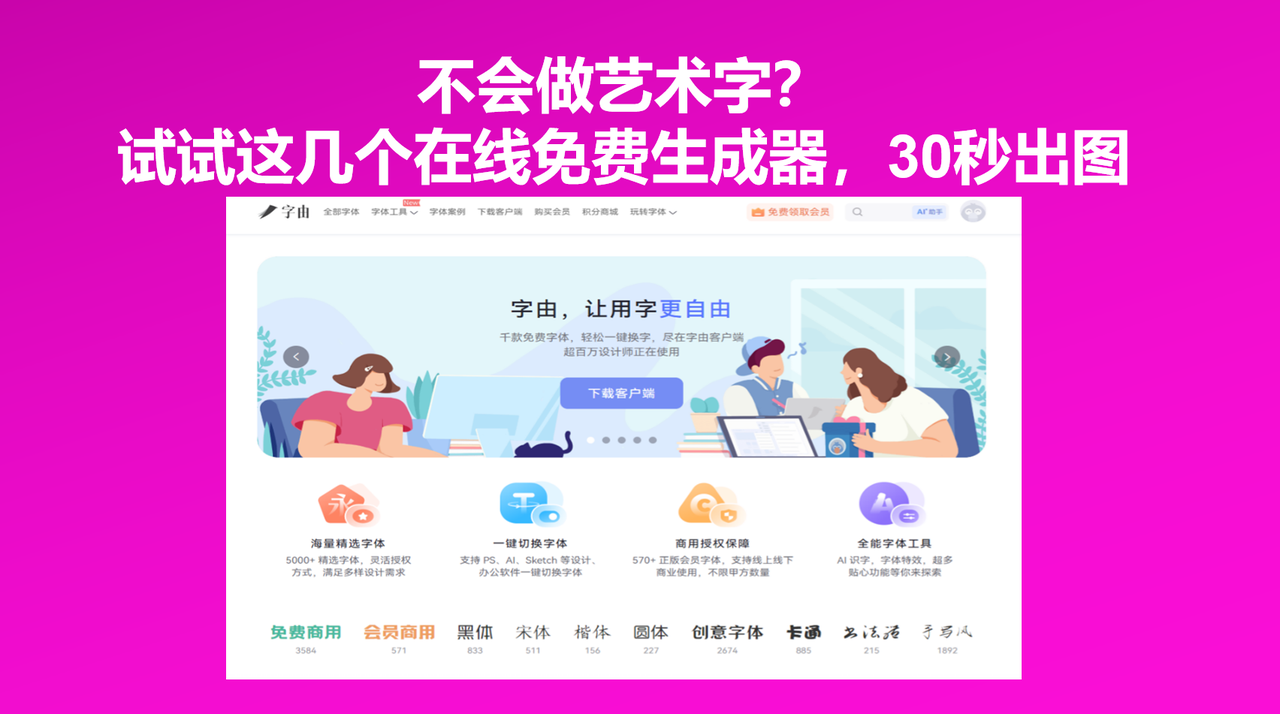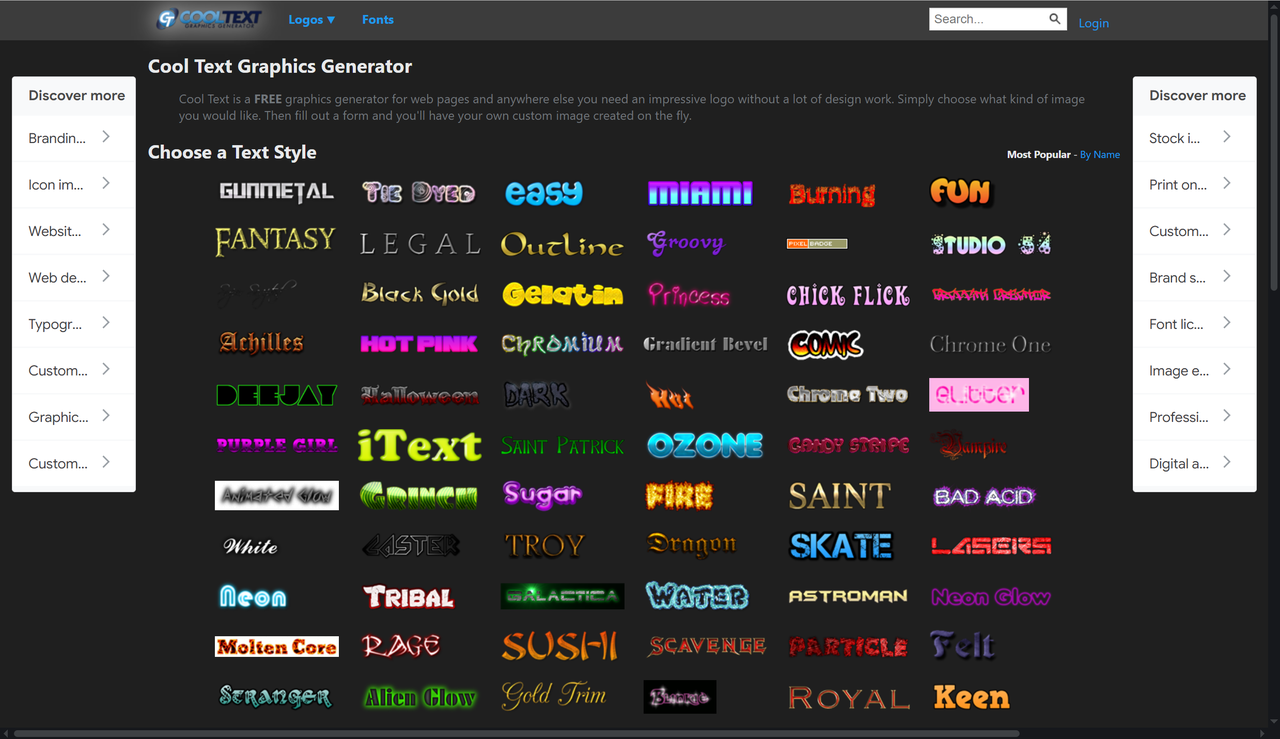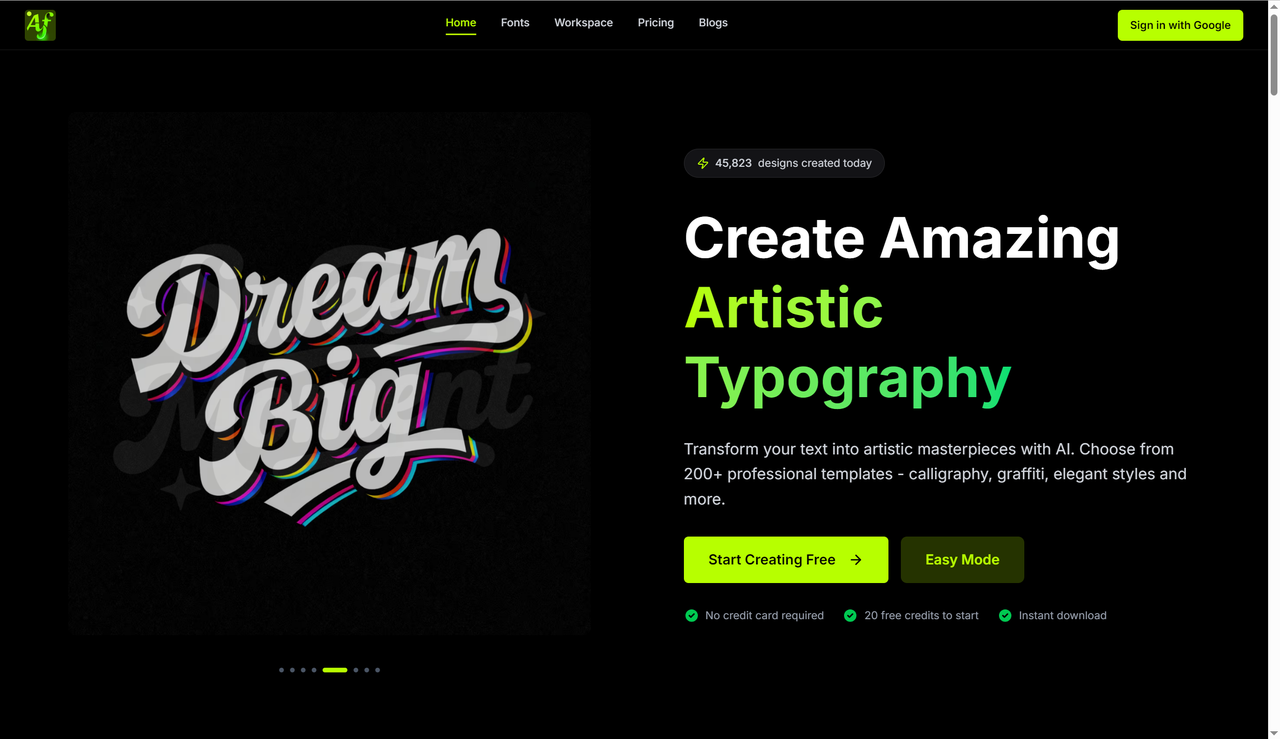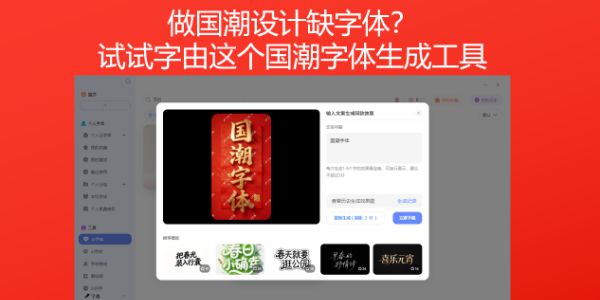
不会做艺术字?试试这几个在线免费生成器,30秒出图
字体的艺术效果可以在很大程度上为画面效果添加艺术色彩,比起一般的传统字体要更加生动活泼。之前可能有很多新手想要艺术字,都会遇到以下困境:想自己设计吧,没那功底;去网上搜字体吧,下载安装太麻烦;用PS调效果吧,调了半天还是不对味。但是在当下互联网和AI工具这么发达的时代,完全不需要手搓艺术字,可以直接用艺术字在线免费生成器,打开网页,输入文字,选个风格,点一下,几十秒就能拿到一张带特效的艺术字。今天我就会推荐5 个亲测好用的艺术字在线免费生成器,以后做图再也不用为字体发愁。
字由不仅有客户端,它的网页版也支持艺术字在线免费生成。你不需要安装任何软件,打开浏览器,进入字由官网,找到【AI字体】功能,就能开始设计。整个过程完全在线,输入文字,选择模板,实时预览效果,最后下载透明背景PNG。接下来我会教大家详细的应用步骤:
- 第一步:进入字由官网(hellofont.cn),在导航栏找到【字体工具】→【AI工具】→【AI字体】。
- 第二步:在搜索框里输入你想要的效果,比如“霓虹”“金属”“手写”“国潮”“3D”,系统会筛出对应的模板。每个模板都有预览图,鼠标滑过就能看到用你的文字实时展示的效果。
- 第三步:选一个顺眼的模板,点击“做同款”,把模板里的文字换成你的标题(最好和模板字数一样)。点击“立即生成”,等20-30秒,就能拿到一张高清艺术字图片。
- 第四步:生成后可以下载透明背景PNG,直接拖进PS、Canva、剪映里用。不需要抠图,不需要调色,模板里都给你做好了。
如果你还想给字体加一些特效,不放也去试试AI字效,内置400多种特效模板,点一下就能加,不用自己调图层样式。同样是透明背景PNG,拖进设计软件里直接用。
2、Cool Text
点进这个网站大家肯定会觉得这个网站有点年头了,没错,Cool Text 是一个运营了二十多年的老牌艺术字在线免费生成器,很多设计师第一次做艺术字就是从它开始的。它的风格分类非常丰富:GUNMETAL、FANTASY、LEGAL、OUTLINE、Black Gold、HOT PINK、CHROMIUM等等,足足有几十种,它的操作也非常简单,选一个风格,填上文字,调整参数,点生成,就能拿到一张艺术字图片。虽然界面有点复古,但胜在经典稳定,效果也够用。如果你需要快速生成各种风格的艺术字,它是个不错的选择。
3、Best Wishes
Best Wishes 是一个AI驱动的艺术字在线免费生成器,首页显示的“45,823 designs created today”,说明用的人不少,也算是一个受大众认可的艺术字免费生成网站。而且它提供200多种专业模板,分为几大类:
- Calligraphy:传统书法和优雅手写体
- Street Art:城市涂鸦和喷漆风格
- Neon Glow:霓虹灯效果
- Elegant Minimal:简约高级风
- Retro:60-90年代复古风
4、Font Generator & 3D Text Effects
这个网站也是我经常用到的老朋友了,它是一个功能非常丰富的艺术字在线免费生成器,提供几十种字体特效,包括:Gold、Neon、Metal、Fire、Retro、Comic、3D、Graffiti、Tattoo、Glitter……几乎覆盖了所有常见的艺术字风格。操作也很简单:输入文字,点一下你想要的特效风格,系统就会自动生成对应的效果图。首页还提供了热门模板,比如“Happy Easter Day”“World Water Day”“Happy Birthday”“Back to School Sale!”等,可以直接套用或参考。生成后可以下载或分享,完全免费。
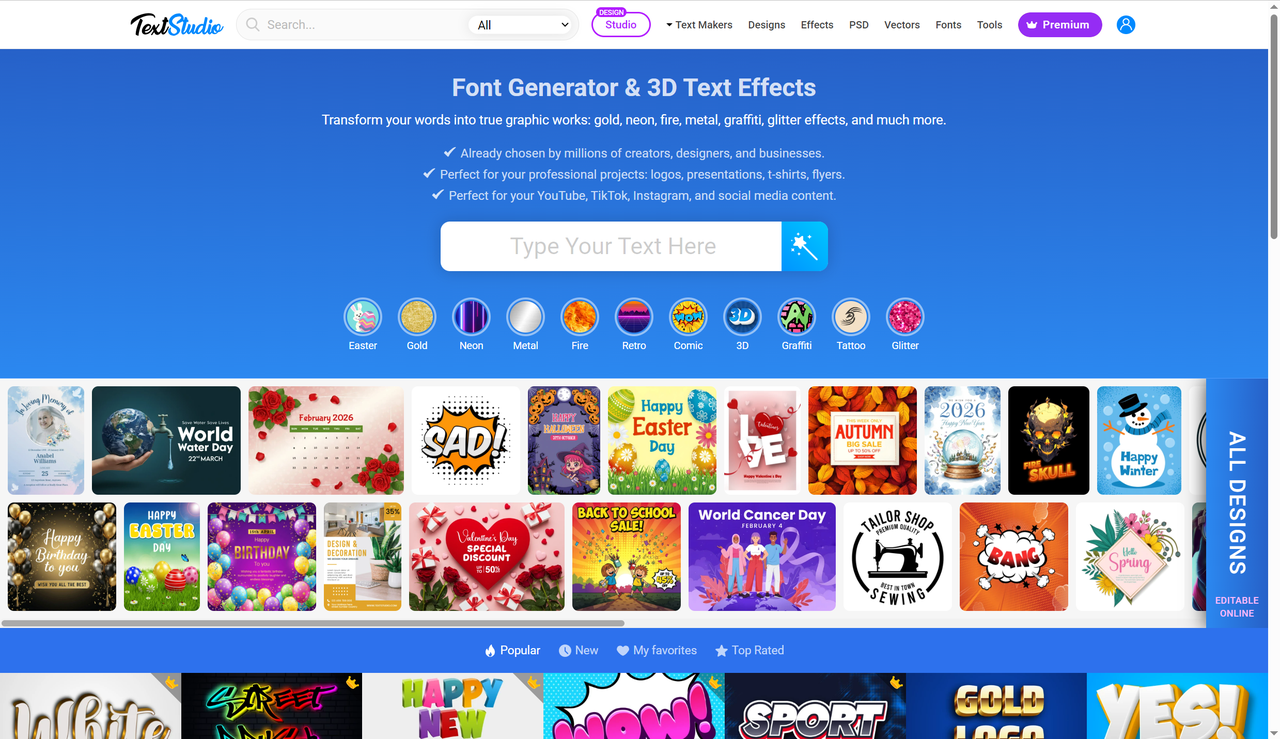
5、Online Art Fonts
这个网站是专门为社交媒体设计的艺术字在线免费生成器,它的核心功能是把普通文字转换成各种风格的装饰字体,适合用在 Instagram、TikTok、Facebook、Twitter 等平台。并且操作极简:在输入框里粘贴或输入文字,系统会自动生成十几种不同风格的字体样式。你挑一个喜欢的,点旁边的“复制”按钮,就能直接粘贴到社交媒体里。支持的语言包括中文、英文、日文、韩文等,完全免费,无需注册。如果你需要的是可以在评论区、个人简介、帖子里直接使用的艺术字,而不是图片格式,这个工具会很方便。